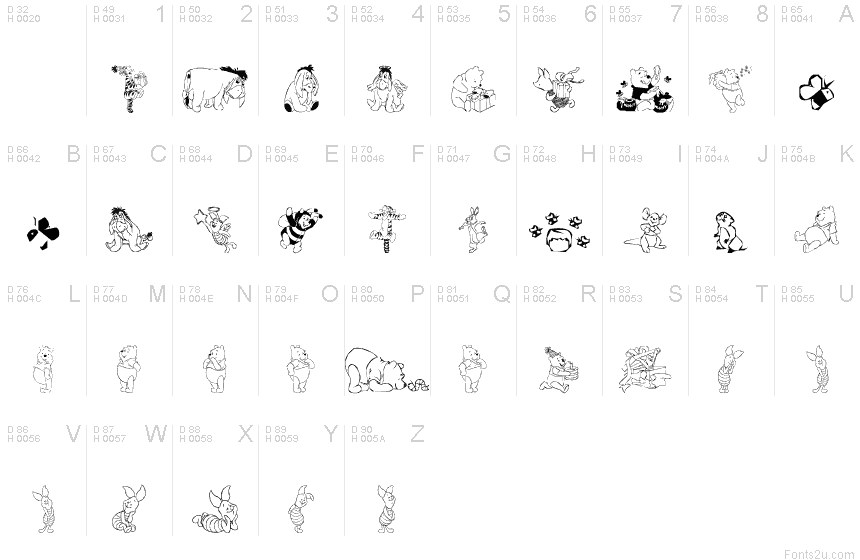
New Pooh هو خط "دينغبات" (رسومي) مجاني من عام 1998 يضم حيوانات كرتونية، ومبني حول دب لطيف من قصص الأطفال مرسوم بخطوط سوداء خفيفة. تبدو المجموعة أقرب إلى الرسوم التوضيحية المرسومة بالحبر منها إلى الحروف التقليدية، بفضل وضعياتها المستديرة وتعبيراتها الناعمة والدودة الصغيرة المرحة التي تضفي لمسة من البهجة.
يعتبر هذا الخط مثالياً لدعوات الأطفال، وصفحات سجل القصاصات، ولافتات الفصول الدراسية، وقرطاسية حفلات استقبال المواليد، وملصقات الحفلات السريعة، حيث يمكن لهذا الخط المجاني أن يضيف لمسات رسومية ودودة بدلاً من الكلمات. وبما أن الرسومات تبدو كلقطات قصصية صغيرة، فهي تعمل بشكل جيد أيضاً على بطاقات المعايدة، والرسومات بنمط الملصقات، وكتفاصيل تزيينية بسيطة حول العناوين القصيرة أو الأسماء.